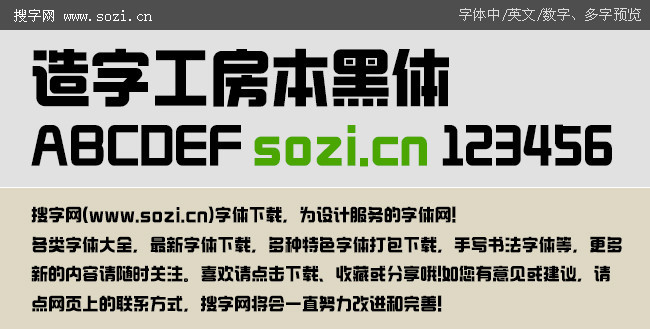
造字工房本黑體
搜字網(wǎng)給大家提供一款造字工房本黑體中文字體下載,造字工房本黑體字形結(jié)體寬闊,章法沉穩(wěn)工整、方圓并舉,于筆畫(huà)轉(zhuǎn)折處巧用圓角,令其風(fēng)格剛?cè)岵?jì),在中正端肅的同時(shí)又不失靜雅溫潤(rùn)之意。在細(xì)節(jié)設(shè)計(jì)上擯棄了復(fù)雜的特點(diǎn),回歸到漢字本身,欣賞方塊字與生俱來(lái)的質(zhì)樸美感。適用于大標(biāo)題、包裝設(shè)計(jì)、海報(bào)設(shè)計(jì)等應(yīng)用。(本字體為個(gè)人非商用版,如需要商用請(qǐng)聯(lián)系官方購(gòu)買(mǎi)版權(quán))